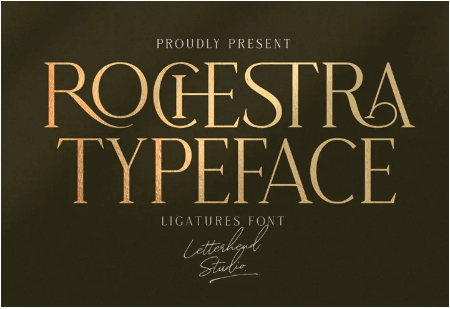
Rochestra Font
Rochestra Typeface — это сложные засечки с уникальными лигатурными символами. Идеально подходит для других различных формальных форм, таких как приглашения, этикетки, логотипы, журналы, книги, поздравительные / свадебные открытки, упаковка, мода, макияж, канцелярские товары, романы, этикетки или любые рекламные цели.